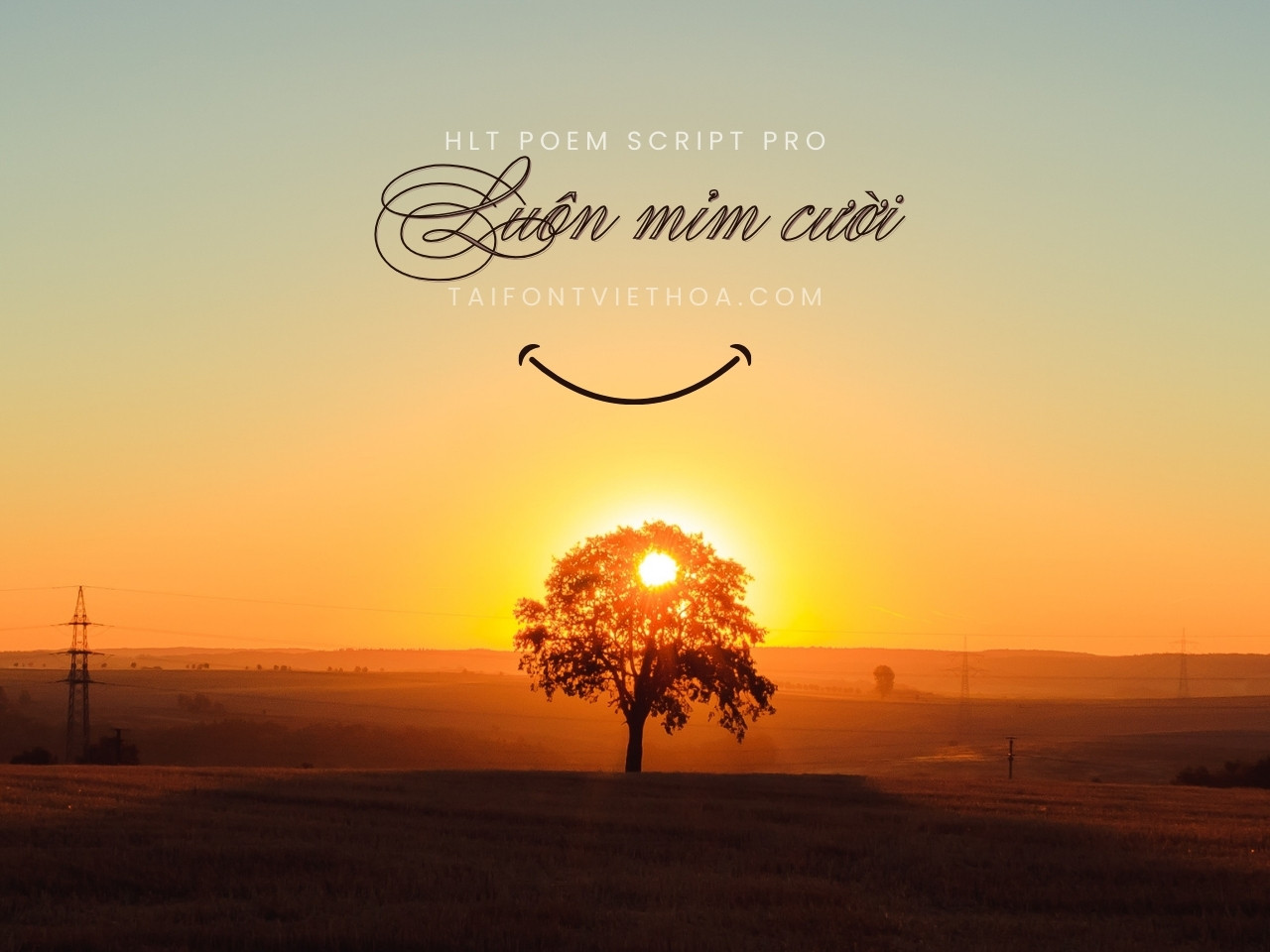
HLT Poem Script Pro – Font thư pháp hiện đại kết hợp nghệ thuật cổ điển
HLT Poem Script Pro là phiên bản Việt hóa của font gốc “Poem Script Pro” – một kiệt tác thư pháp hiện đại được thiết kế bởi Sudtipos, một trong những foundry hàng đầu tại Argentina do Ale Paul sáng lập. Font này là sự kết hợp hài hòa giữa nghệ thuật viết tay kiểu cổ điển với tính hiện đại qua hệ thống glyphs đồ sộ, stylistic alternates và hàng trăm ligatures đặc biệt. Phiên bản gốc hỗ trợ hơn 200 ngôn ngữ sử dụng bảng chữ cái Latinh mở rộng, phù hợp với các thiết kế toàn cầu mang tính nghệ thuật cao.
Font đã được Việt hóa trọn bộ bởi nhóm HLT Fonts, đảm bảo đầy đủ dấu tiếng Việt với độ chi tiết và tính thẩm mỹ chuẩn mực. HLT Poem Script Pro giữ nguyên các đường lượn tinh tế và phong cách bay bổng của bản gốc, mang đến trải nghiệm thị giác ấn tượng khi áp dụng vào thiết kế tiếng Việt. Font này đã được taifontviethoa.com tuyển chọn và chia sẻ đến cộng đồng thiết kế, phục vụ thực tiễn trong các dự án sáng tạo cần sự mềm mại và sang trọng.
Đặc điểm thiết kế, ứng dụng và ngành nghề phù hợp
HLT Poem Script Pro sở hữu thiết kế đặc trưng của dòng font calligraphy hiện đại: đường nét bay bổng, liền mạch, ligatures dày đặc và các ký tự thay thế đa dạng mang lại sự biến hóa không giới hạn. Font có độ dày trung bình, độ tương phản cao, tạo cảm giác quý phái và tinh tế trong từng dòng chữ. Đặc biệt hiệu quả khi sử dụng cho tiêu đề, trích dẫn, thiệp cưới hoặc logo mang dấu ấn cá nhân mạnh.
Font thích hợp cho các dự án thiết kế cao cấp như bộ nhận diện thương hiệu mỹ phẩm, spa, sản phẩm thời trang, wedding planner, blog cá nhân, ấn phẩm nghệ thuật, thiệp mời sự kiện hoặc bao bì sản phẩm cần truyền tải thông điệp bằng cảm xúc và chất riêng.